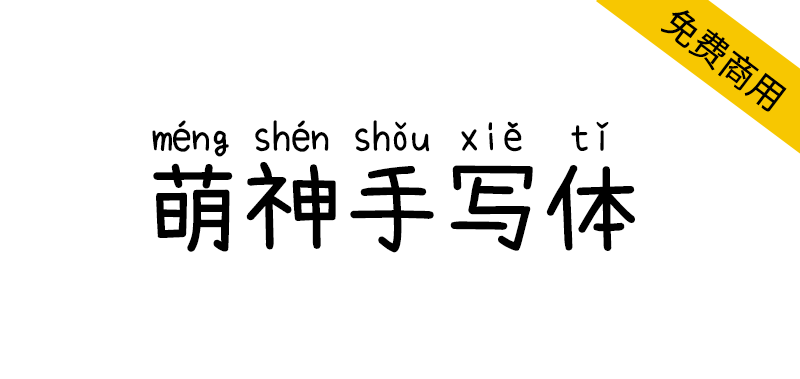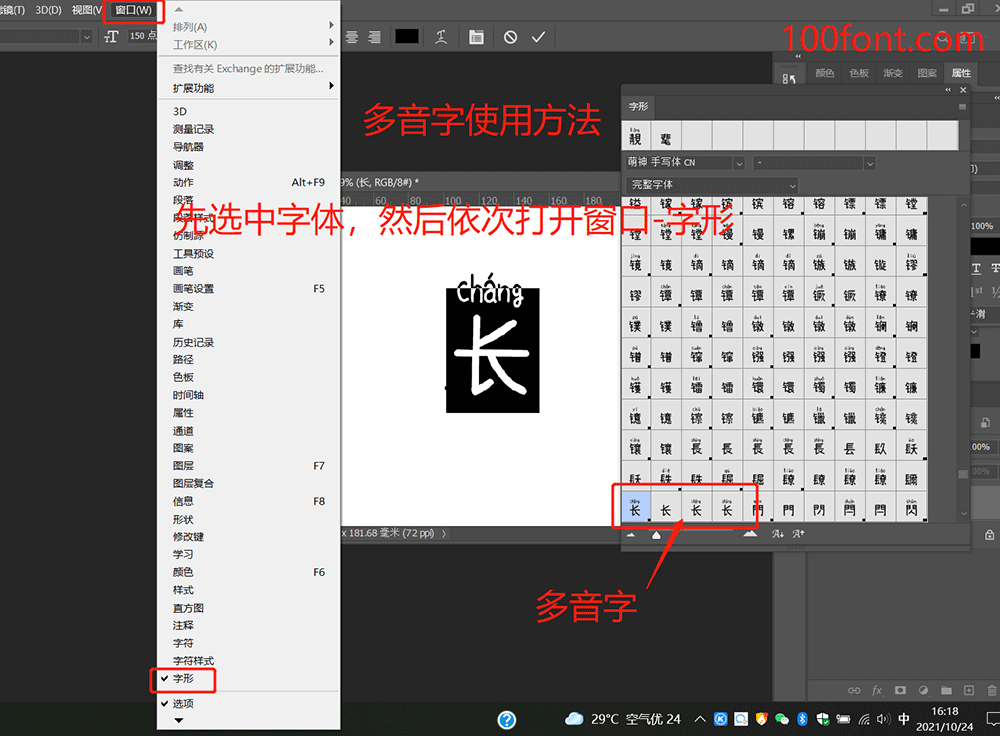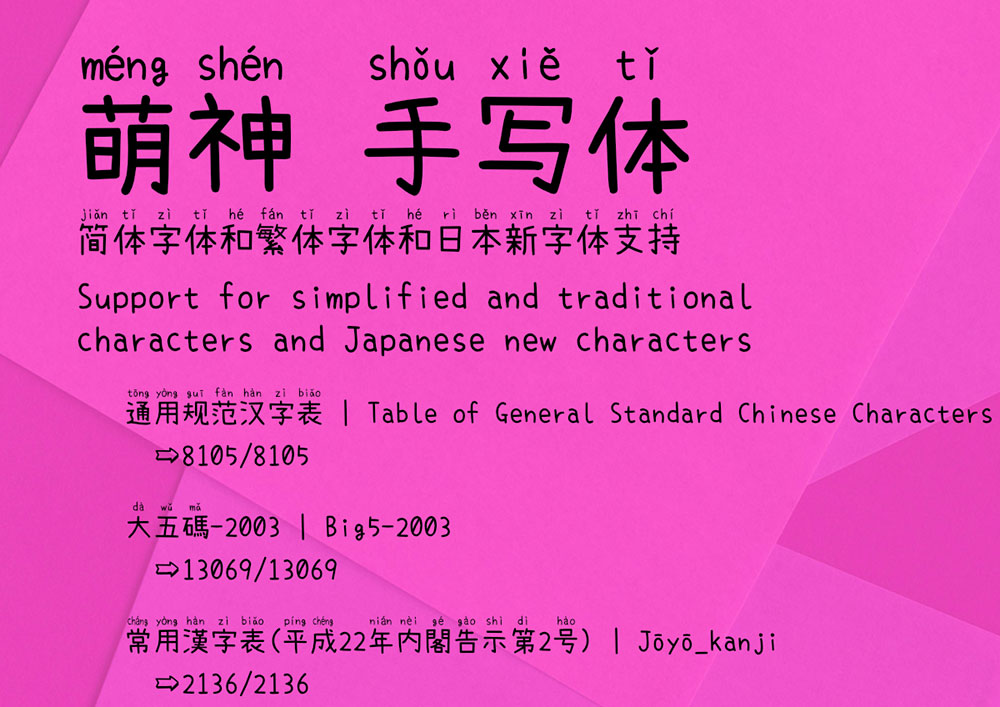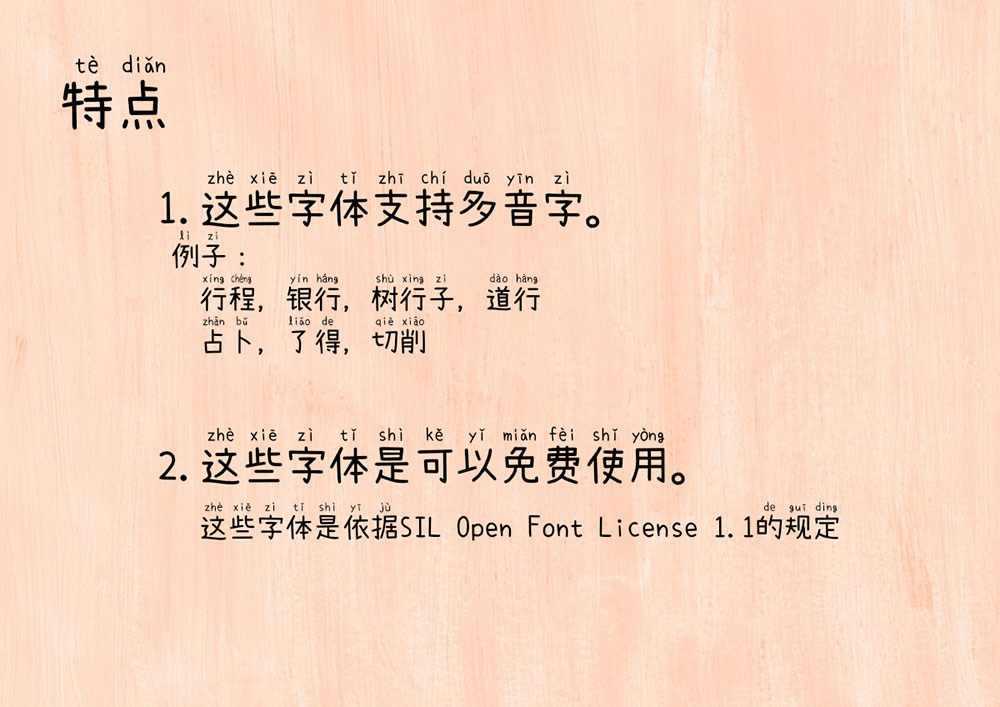
萌神手写体是由小赖字体进行改造而成的一款拼音字体,手写风格,自带拼音,支持多音字,采用SIL Open Font License 1.1授权协议发布。这是一款能够显示基础日语、简体中文及繁体中文的字体,并且专门为简体和繁体汉字均添加了拼音注音的字体设计,适合用于帮助学生更快地学习和阅读汉语。
萌神手写体实现了上下文替换(feature of“rclt”at GSUB)以支持多音字。另外,还可以使用Unicode IVS(表意文字变体选择器)来切换到不同的拼音。